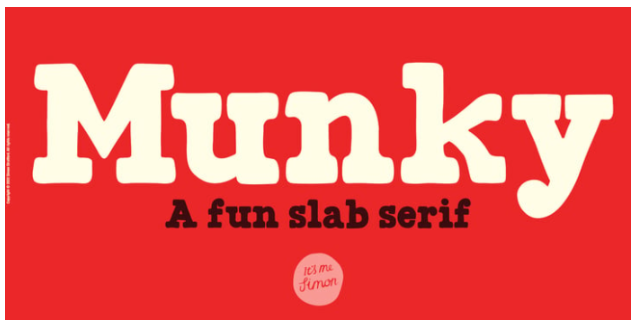
Munky - большая чаша, наполненная добрыми засечками. У него дерзкий, игривый вид с крупными, тяжелыми засечками. Его формы имеют несколько перегибов то тут, то там. Я бы сказал, что это добавляет ему шарма - и это так.
Он отлично подходит для заголовков и названий, но также очень разборчив в предложении.
Он отлично подходит для брендинга и упаковки, книг, приглашений и всего, где требуется непринужденная атмосфера, но не слишком детская.
Если бы шрифт был знаменитостью, он был бы скорее Джоном Кэнди, чем Джоном Малковичем.